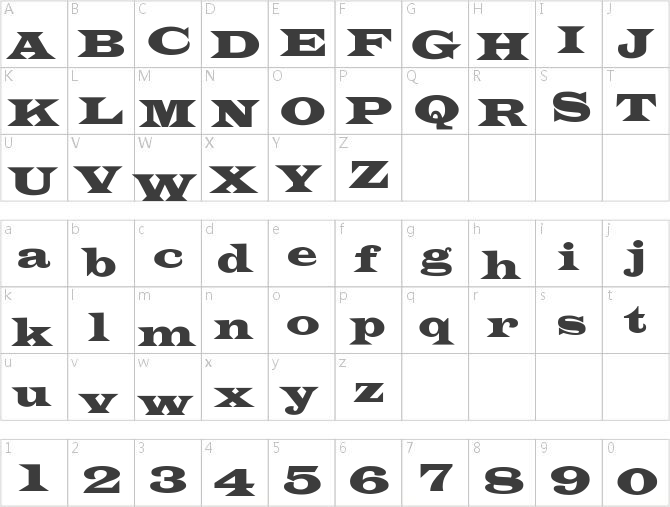
JamesWideCnd-No
JamesWideCnd-No介紹
JamesWideCnd-No字體字庫是一款讓人賞心悅目、百看不厭的英文字體,適合各類廣告和產品包裝設計應用,字體大小0.03MB,格式為ttf字體,上傳用戶是gagilang,作者/版權方為未知
JamesWideCnd-No效果圖